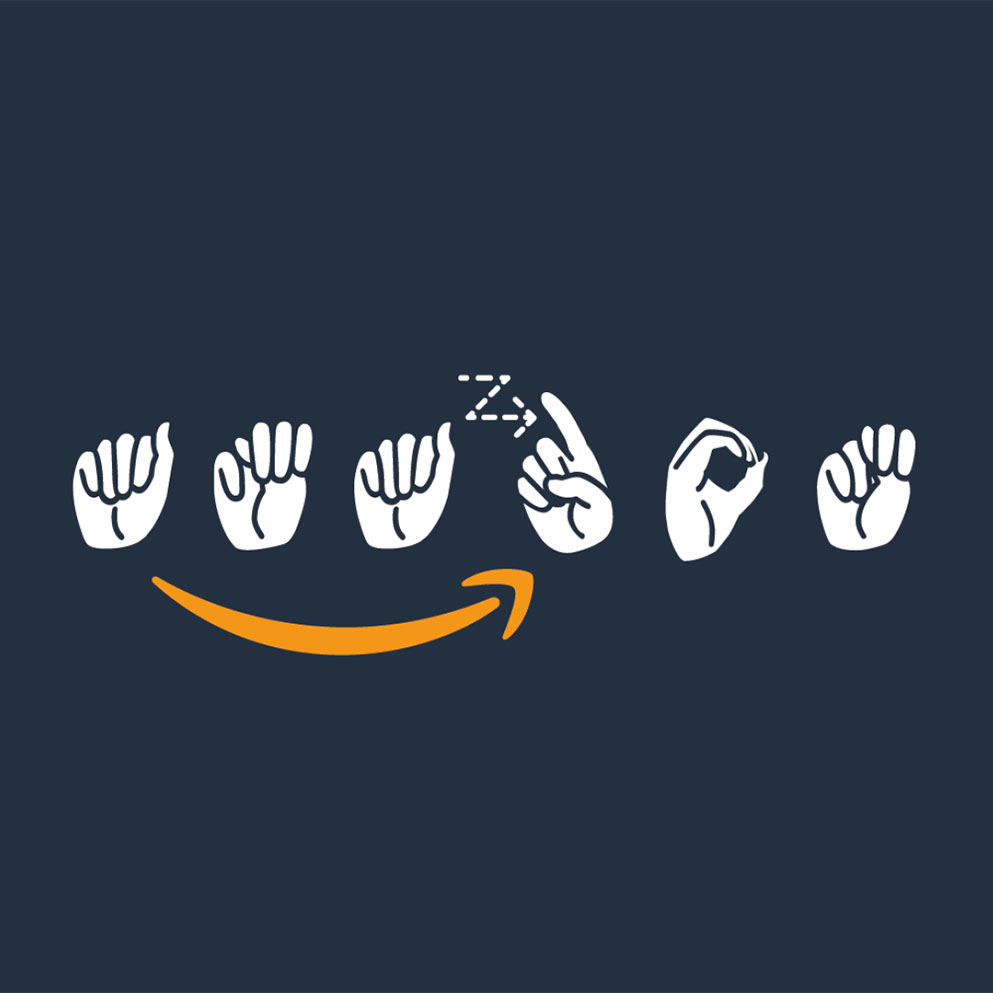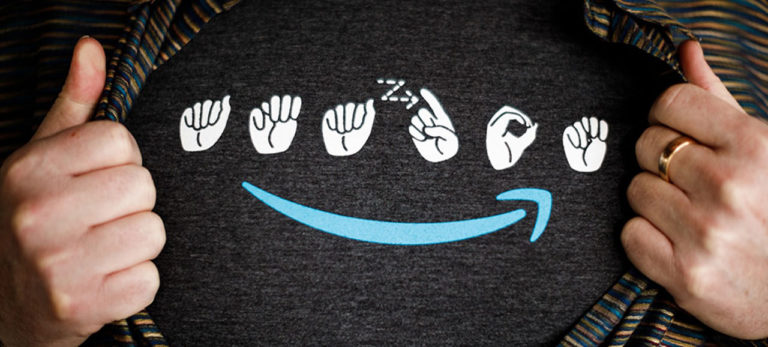
아마존, 청각 장애인을 위한 수화 버전의 로고 공개
아마존의 고객 결제 대응팀의 UX 디자이너, 브렌든 그래머의 노력으로 아마존의 수화 버전 로고가 탄생했다. 이 팀은 고객을 위한 결제 경험을 디자인한다.
아마존 내부의 청각 장애인이나 수화를 배우는 직원들을 돕고자 하는 마음에서 출발해 수화 로고를 개발하게 됐다고 그래머는 밝혔다.
그는 “문화적으로 긍정적이면서도 진실한 아마존 직원들의 포용력을 담아내고 싶었다”고 덧붙였다. 아울러 그는 아마존 PwD(장애인)가 이미 지역 사회에서 청각 장애인을 포용하고 정체성을 부여 받을 수 있도록 노력했기 때문에 좋은 출발점이 되었다고 했다.
그래머는 디자이너를 포함한 다양한 팀원들과 아마존 수화 로고 디자인을 주도해왔다. 손가락으로 표현한 스펠링 동작을 정확하게 보여주기 위해 함께 영어 문자로 번역했다.
로고는 단순히 상징적인 것만이 아니라 유용한 도구이다. 예를 들어 포스트 홀리데이 파티에서 청각 장애인 참석자들이 의사 소통에 대한 도움을 받을 수 있도록 배지를 받아 착용했다. 그리고 그래머는 말했습니다. “아마존 내에서 수화 로고의 인식과 확산을 위해서라도 관련 직원과 수화 통역사를 계속해 채용할 것”이라고 말이죠. 그리고는 CSR의 약속은 “로고에 대한 모든 긍정적 반응을 보기 위해 관련 모임이 활발히 진행되도록 지원할 것”이라고 말했다”.
10년 가까이 일한 아마존에서 그래머는 아마존 내 장애인 직원들의 친목 모임을 주도했고, 그들이 사회 활동에 더욱 적극적으로 참여할 수 있도록 노력해왔다.
그래머는 시카고 외곽의 한 가정에서 태어나 청각 장애인으로 태어났다. 그의 부모는 입술을 움직여 구두로 말을 하도록 하는 습관을 기를 수 있도록 권면했고 그는 수화 보다는 이러한 방식을 선호하기도 했다. 하지만 그는 수화를 배우고 난 뒤 그의 인생에서 중요한 점을 놓치고 있다는 것을 깨달았다.
학창 시절, 그는 선생님은 학교 종이 울리면 크게 소리를 지르며 말씀했기 때문에 숙제에 대해 자세히 이해하지 못했다고 했다.
그는 평생 얻은 교훈으로 아마존에서 열정을 쏟아내 결국에는 청각장애인들과 수화를 배우고자 하는 이들과 티타임을 갖고 열심히 수화를 가르칠 것이라고 포부를 밝혔다.
그는 모든 이에게 열린 마음을 가질 것이다.